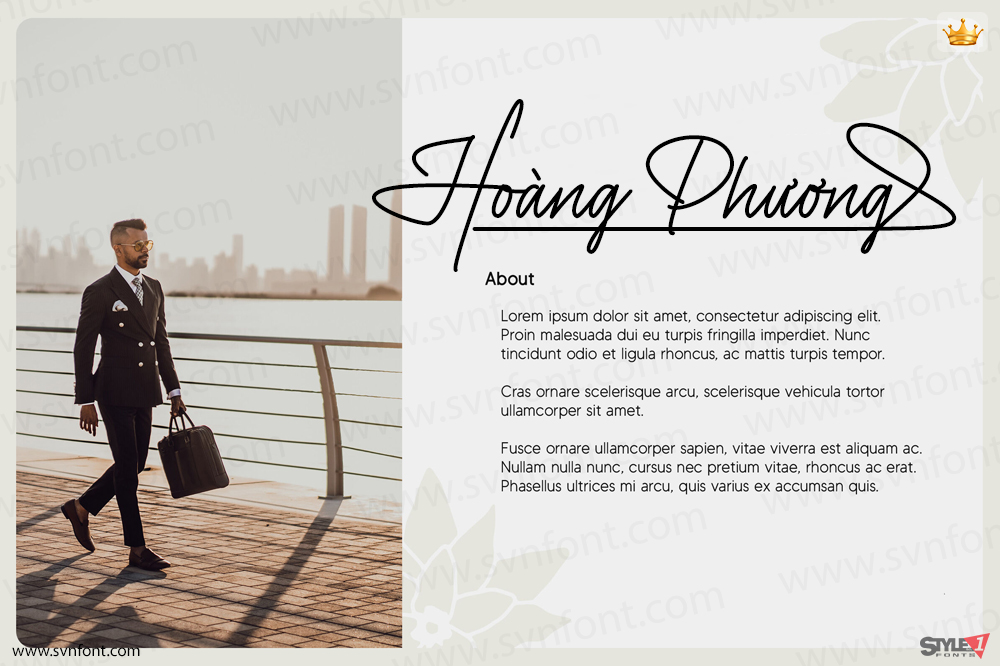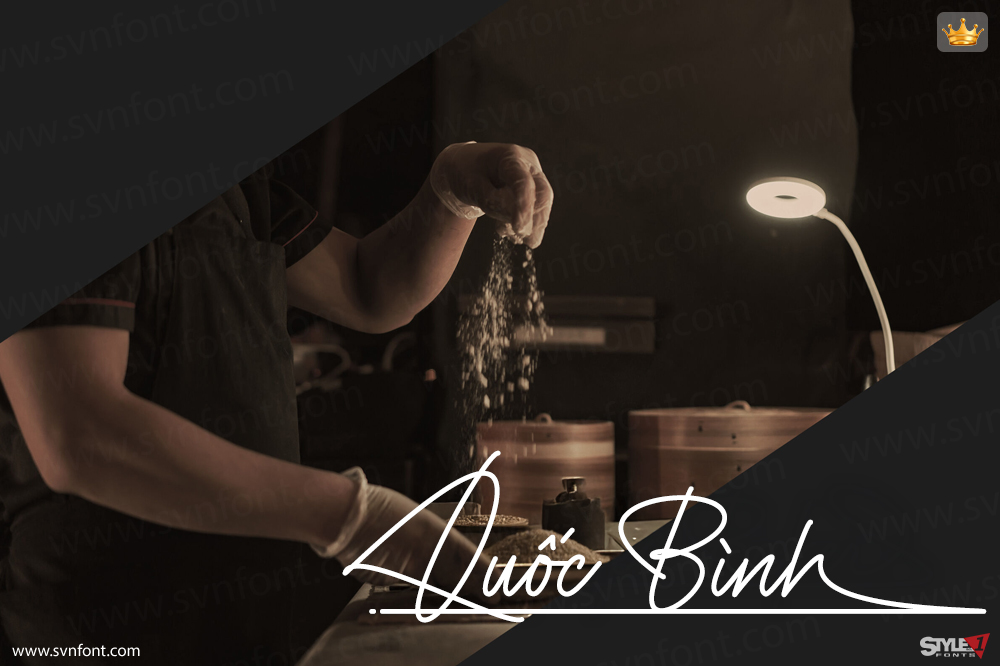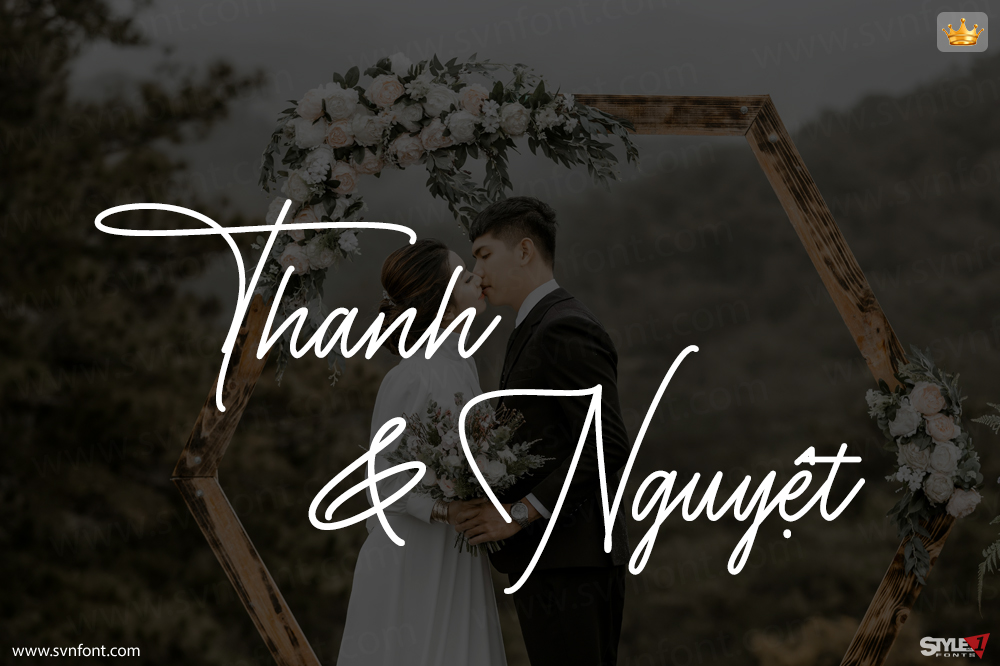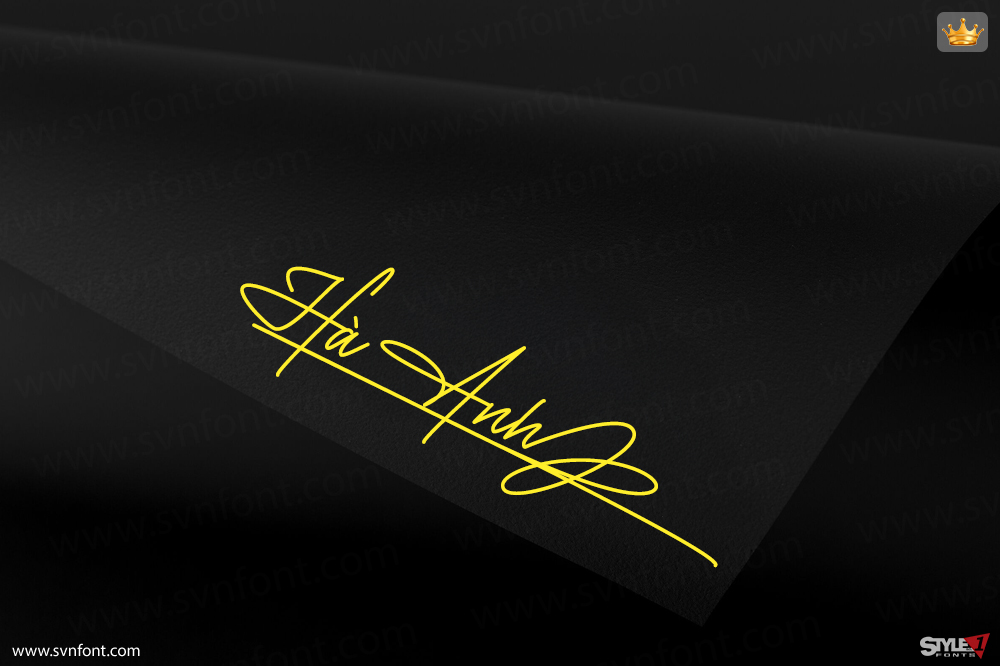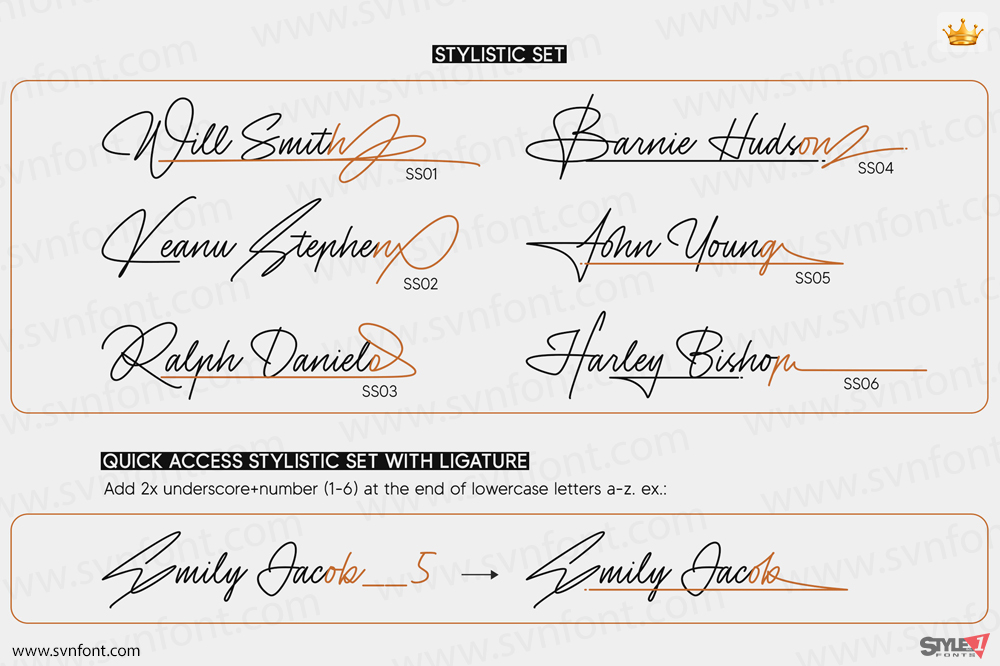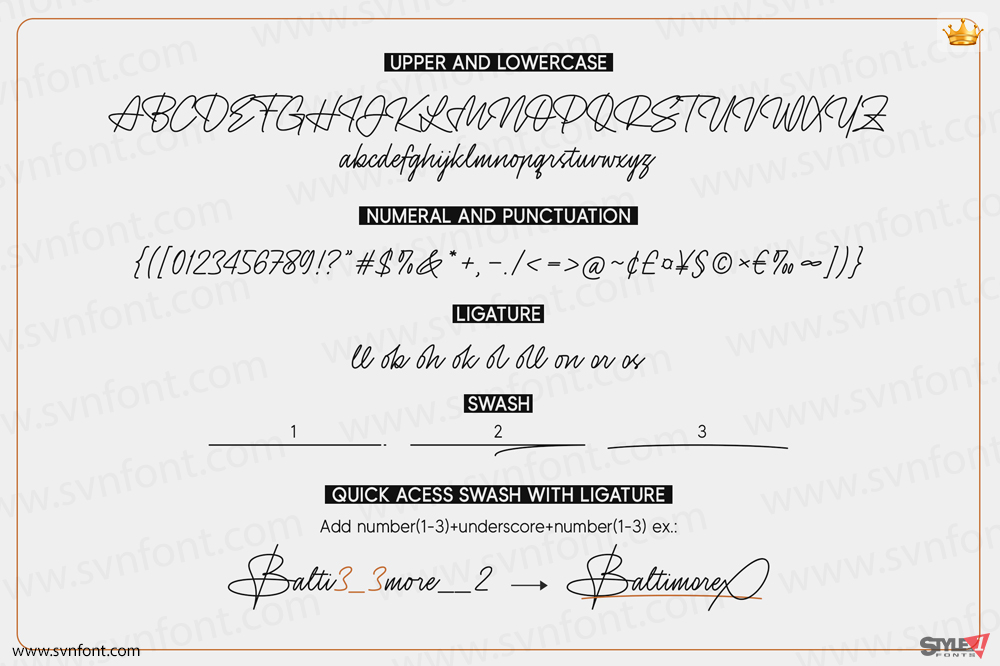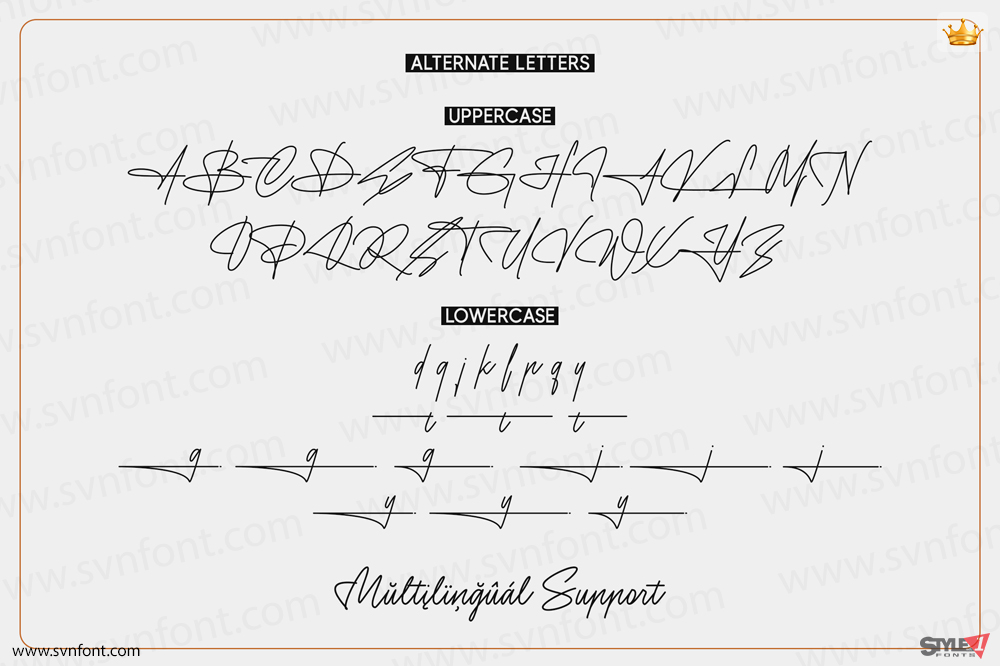
Sinatra là một phông chữ chữ ký thanh lịch với phong cách đơn nét, mang một dòng chảy đáng yêu. Nó có một cảm giác sạch sẽ, mảnh mai và mượt mà, và nó sẽ là một điểm nhấn cho bất kỳ thiết kế nào bạn muốn thêm vào. Nó hoàn hảo cho nhiều dự án khác nhau như logo và xây dựng thương hiệu, thiệp mời, chữ ký, nhãn mác, nhiếp ảnh và hơn thế nữa!
Nhà thiết kế: Dwi Ahidian
Nhà phát hành: Lemonthe Type